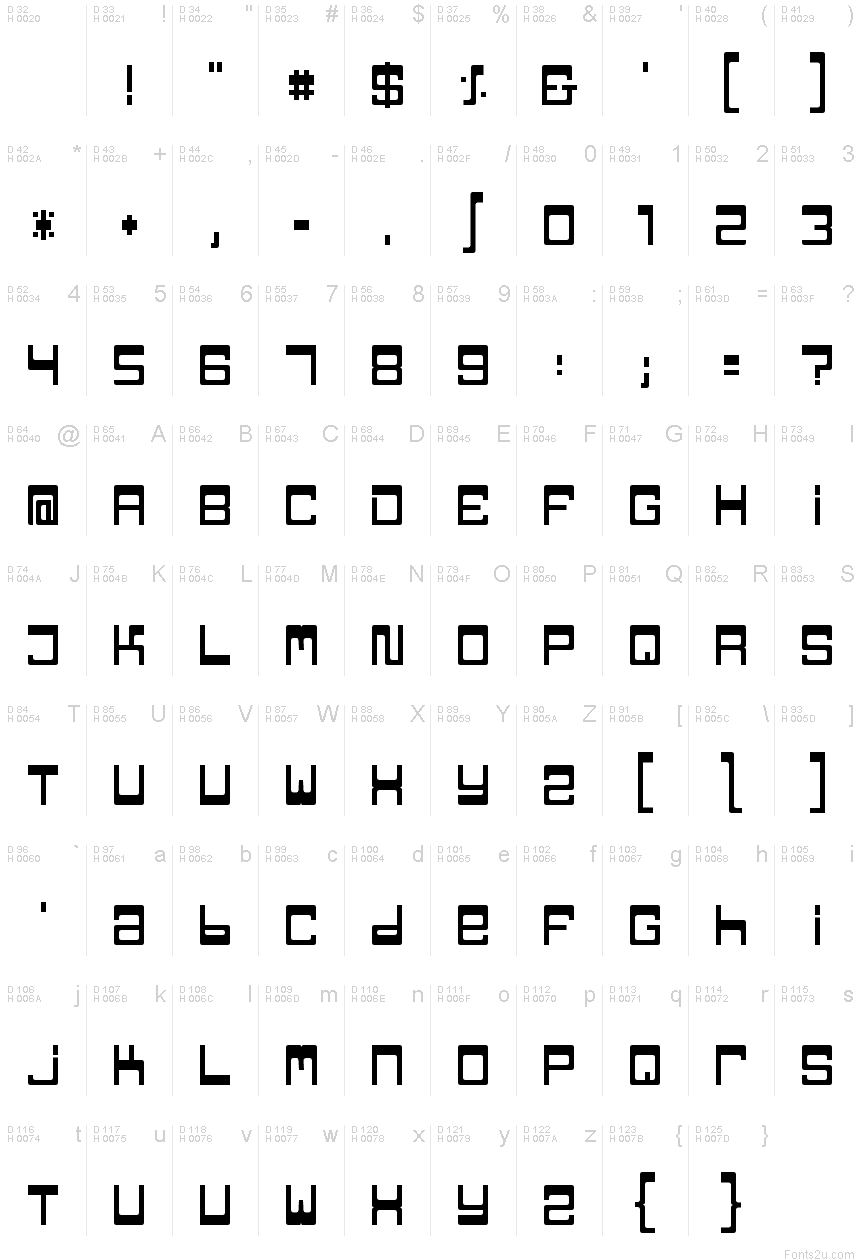
TPF Jaib autorstwa Christopha Scheiblhofera to nowoczesny, darmowy krój displayowy z wyrazistym, technologicznym pulsem. Litery wyglądają, jakby zostały zbudowane z ciężkich, kwadratowych elementów, ale zaokrąglone wcięcia i szerokie, poziome formy sprawiają, że projekt nie wydaje się zimny. Nadaje to krojowi zabawny, cyfrowy rytm, sytuujący go gdzieś pomiędzy estetyką gier arcade a futurystycznymi znakami słownymi.
Świetnie sprawdza się na plakatach muzycznych, w tytułach gier, na ulotkach klubowych, w brandingu technologicznym oraz w krótkich nazwach na opakowaniach, gdzie ten kompaktowy, zazębiający się styl potrafi udźwignąć cały komunikat. Jako darmowy font, sprawdzi się również w tekstach na okładkach, planszach tytułowych i szkicach logotypów, które wymagają odważnej, modularnej faktury bez zbędnych ozdobników.
TPF Jaib